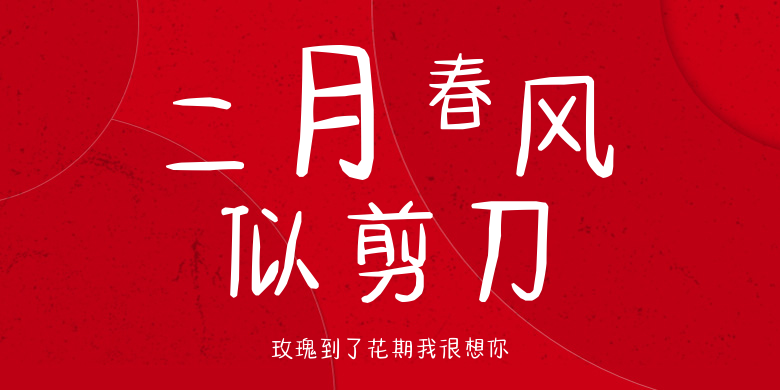
玫瑰到了花期我很想你
玫瑰到了花期我很想你,这款字体结构工整、笔画清晰,兼顾美观与易读性,适用于标题、正文、海报、包装、LOGO 等多种场景。字形优雅稳定,风格百搭耐看,适配日常排版与创意设计,让文字呈现更舒适、更具质感。玫瑰到了花期我很想你一笔一画,皆是细节,以均衡的比例、流畅的线条打造舒适视觉体验,字形端正大气,风格简约现代。无论是商业设计、品牌宣传还是日常排版,都能轻松驾驭,让文字更有格调与力量。玫瑰到了花期我很想你字体下载。